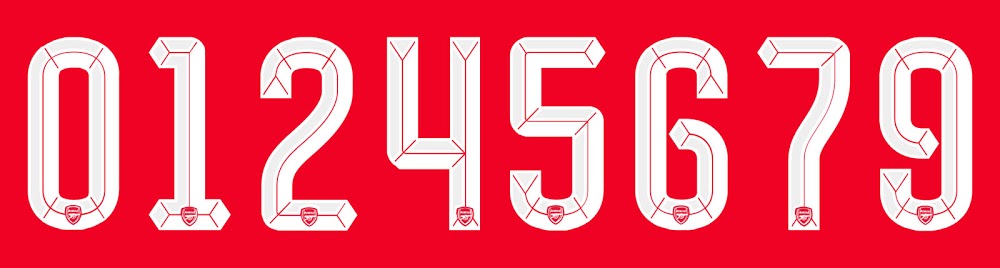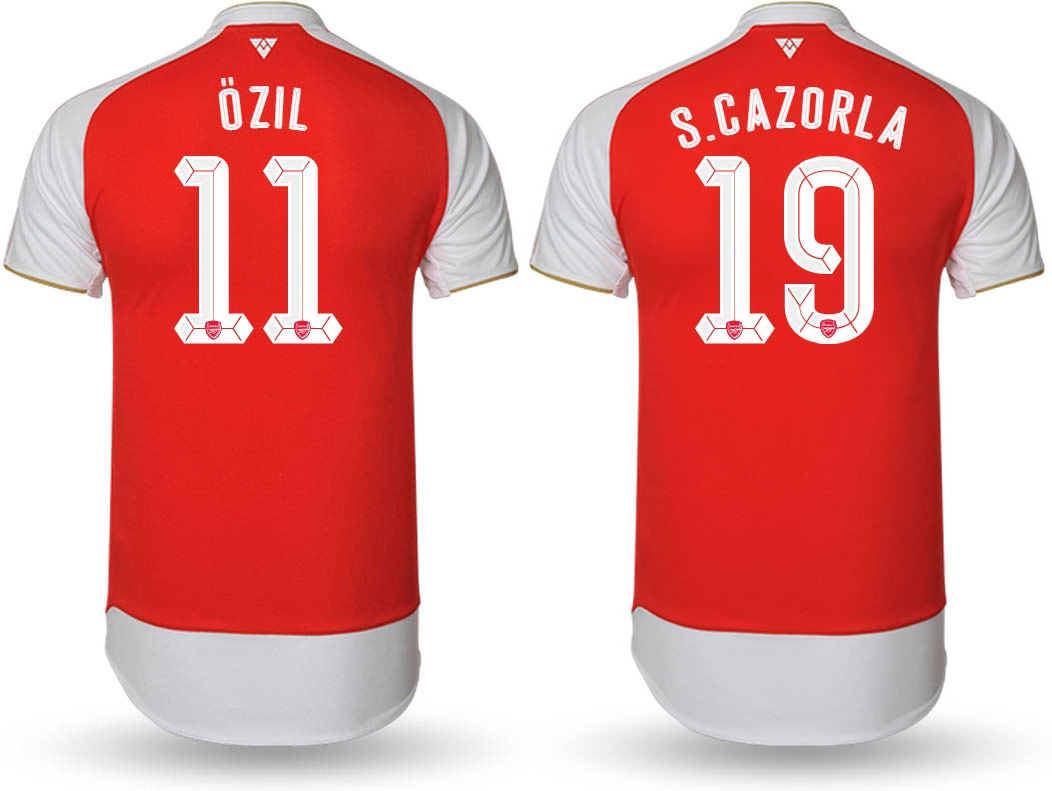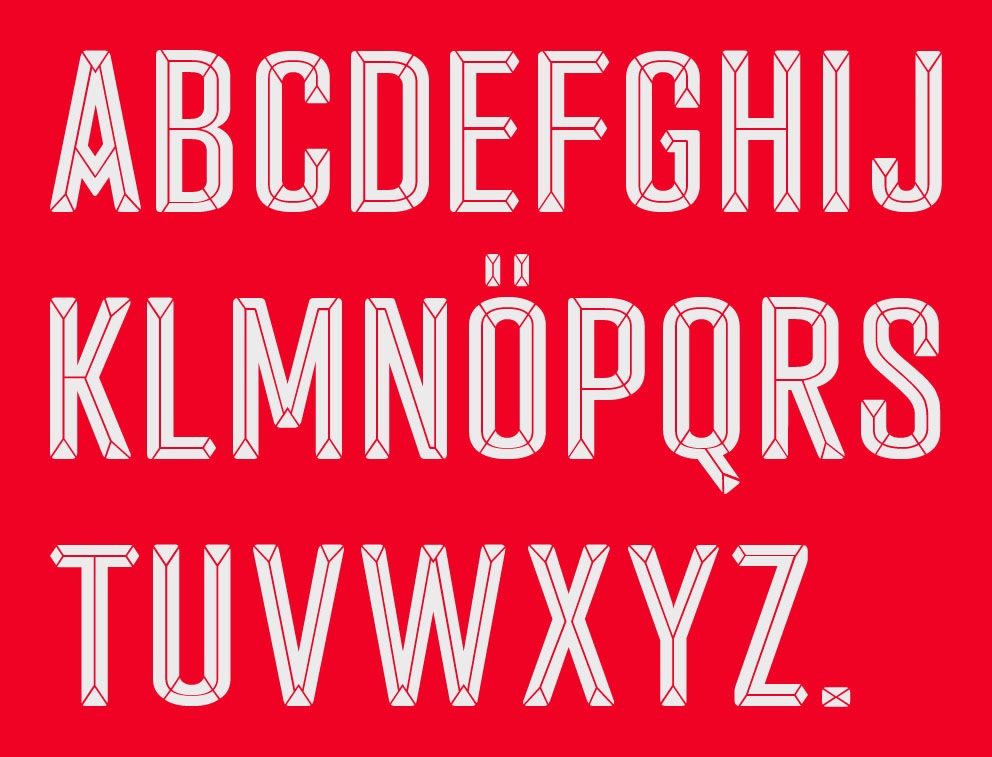
アーセナルが16日に発表した2015-16シーズンの新ユニフォーム。イングランドの名門クラブらしい格調高いデザインが特徴だが、それに合わせたネームやナンバーのフォントも公開されている。
イングランドではプレミアリーグがChris Kay社による共通のフォントを使用しているが、欧州カップを含むその他のコンペティションでは各クラブが自由にフォントを選択できる。
たとえば5月30日に行われたFAカップ決勝ならアストン・ヴィラがリーグ公式フォントだったのに対し、アーセナルはPumaによる独自フォントのユニフォームを使用していた(上の写真はやや分かりにくいが)。
そして、新シーズンに向けてPumaがアーセナルへ提供するフォントがこれだ。
昔の背番号などによく見られた3Dフォントを現代らしくフラットに置き換えたようなデザイン。どの数字も下部にはクラブのエンブレムが入れられている。
アルファベットでは「O」の上に二つの点、ウムラウトがしっかりと存在。もちろんメスト・エジル用である。
エジルとサンティ・カソルラのユニフォームはこんな感じ。ユニフォームデザインとの相性はどう?